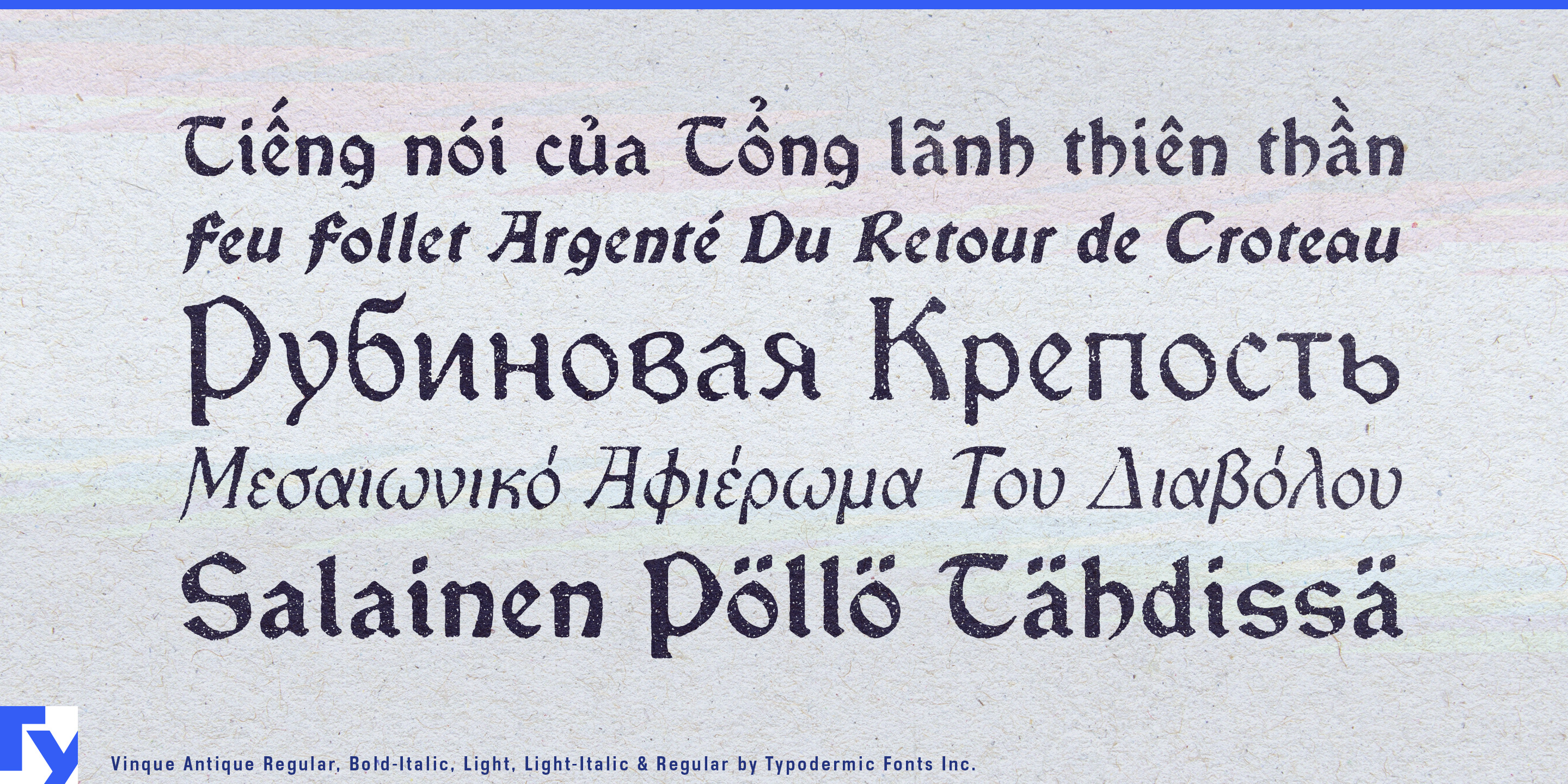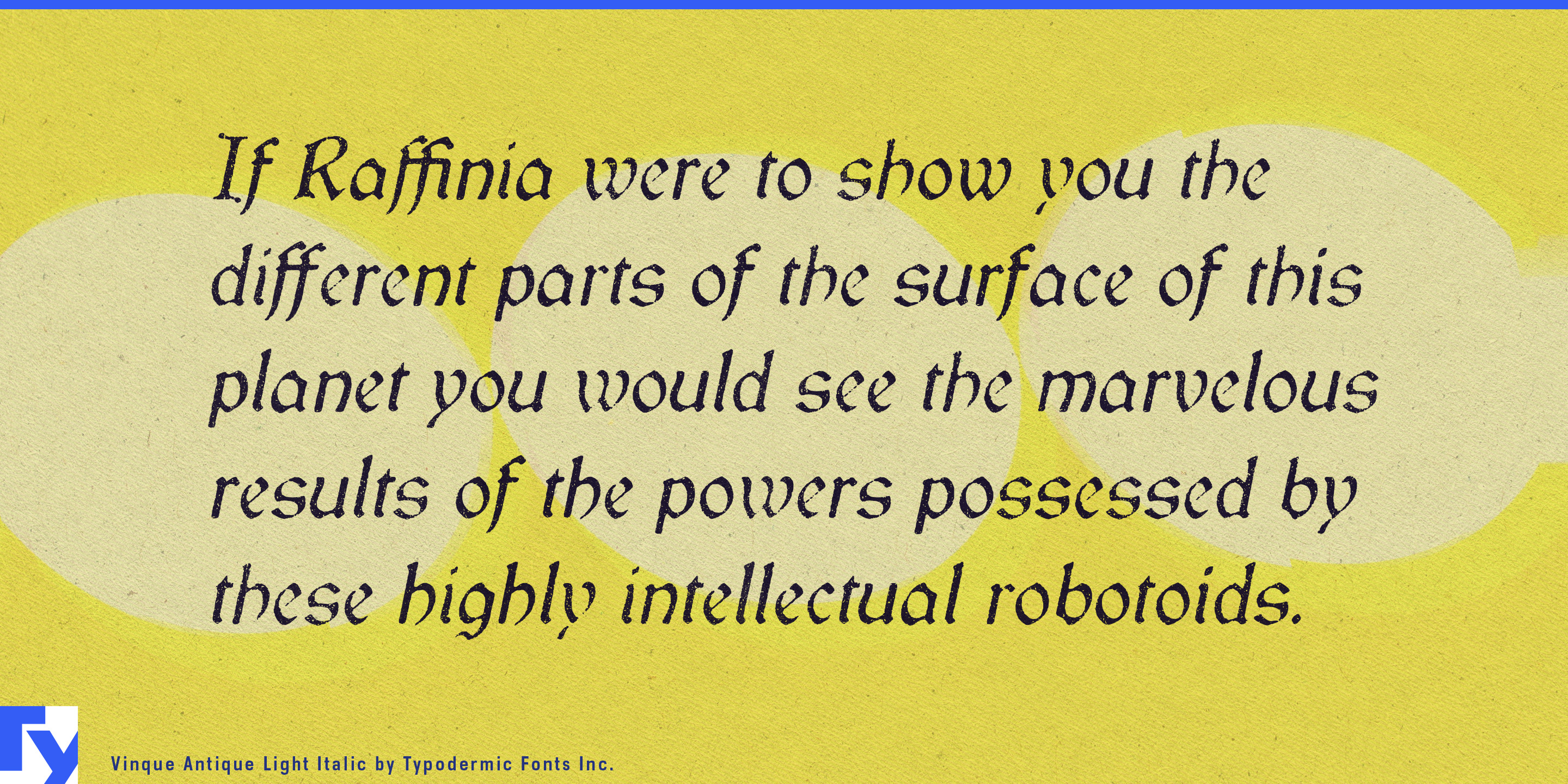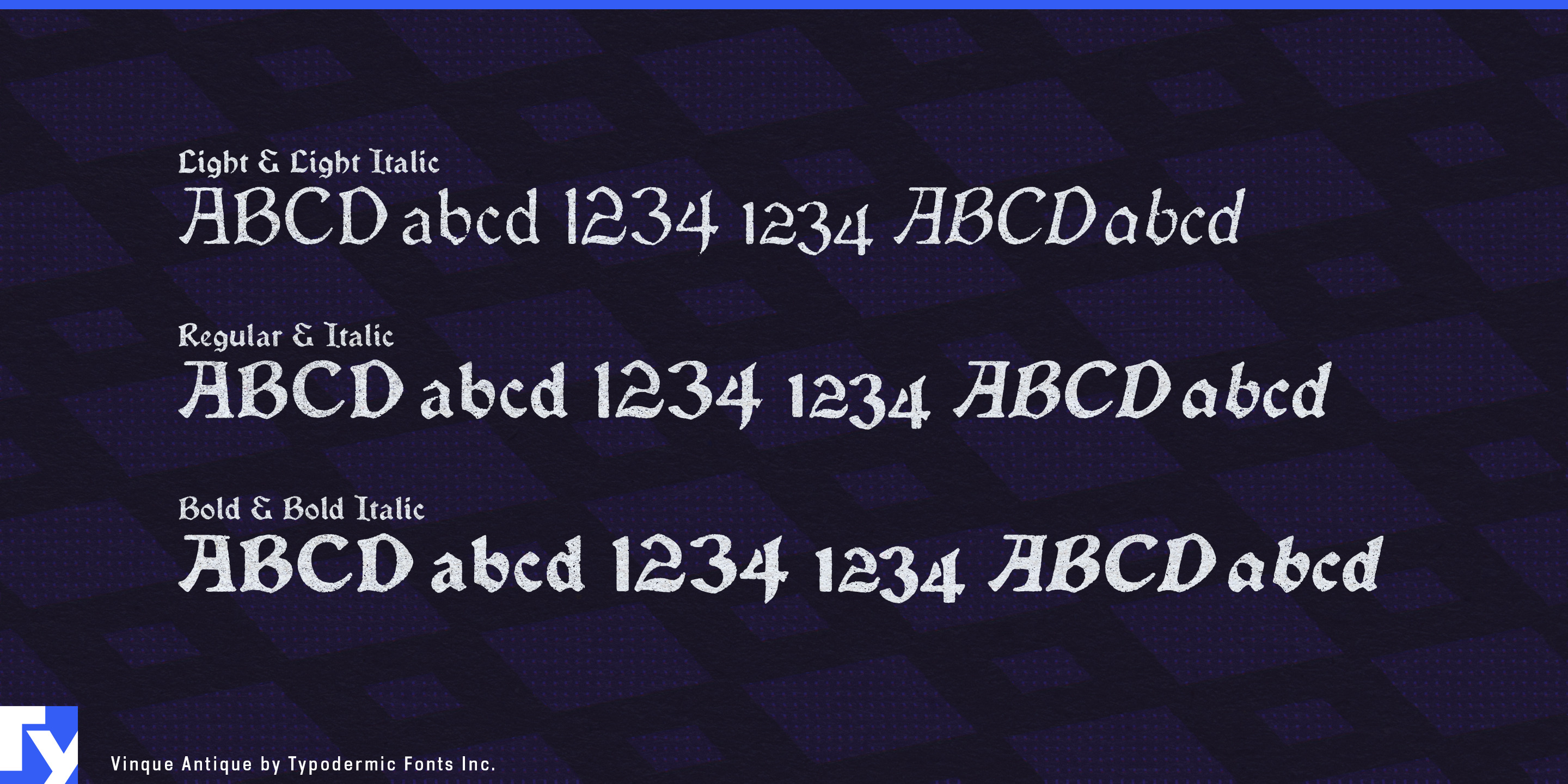
Vinque Antique
Vinque Antiqueは、すでにどこかで使われてきたように見せたいデジタルの文字のための書体です。風化した輪郭は、Vinqueの比較的読みやすい西洋ゴシック系の構造を保ちつつ、不規則な縁と傷んだ表面を加えます。新しく生成した言葉も古地図、傷んだ告知、摩耗した看板、架空の文書になじみます。摩耗の異なる代替字形によって、デジタルで作ったかすれ文字が機械的に押されたように見える反復を抑えます。
そのため、文字が変化しても小道具の説得力を保ちたいファンタジーや歴史ゲームに特に役立ちます。クエストの掲示板では、名前、行き先、怪物、報酬の異なる新しい手配書が生成されるかもしれません。Vinque Antiqueなら見出しやラベルを動的な文字のまま、同じ傷んだ世界に属するように見せられます。
地図にも同じ問題があります。地域名、集落、ダンジョンの入口、航路、キャンペーンの章、発見した場所は、ローカライズ、自動生成、プレーヤーの進行によって変わります。Vinque Antiqueなら、羊皮紙風の地図にその名前を載せても、イラストの上に真新しい画面の文字が浮いているようには見えません。
同じ方法は指名手配ポスター、ギルドの掲示、王の布告、錬金術師のラベル、商人の掲示板、酒場のメニュー、日誌の見出し、魔法書の章、所持品タグ、探検記録、風雨にさらされた銘板にも使えます。サバイバルや探索のゲームでは、廃墟となった集落、放棄された修道院、忘れられた遠征、辺境の交易所、考古学遺跡など、看板や文書が風雨と人の手にさらされ、不完全に見える必要がある場所に合います。
卓上ゲームや没入型エンターテインメントでは、キャンペーン地図、クエストカード、遭遇カードの束、キャラクターの資料、ゲームマスターの配布資料、アトラクションの地図、酒場の掲示、布告、テーマホテルの看板、小道具ラベル、土産物のグラフィックへ同じ素材感を運べます。
Vinque Antiqueは、変わり続ける文字を新しく入力したものではなく、発見されたもののようにします。ファンタジー、伝承、歴史的な雰囲気を、静止画像として一度だけ風化させることのできない地図、告知、看板、ラベル、文書の中で保つときに最も役立ちます。